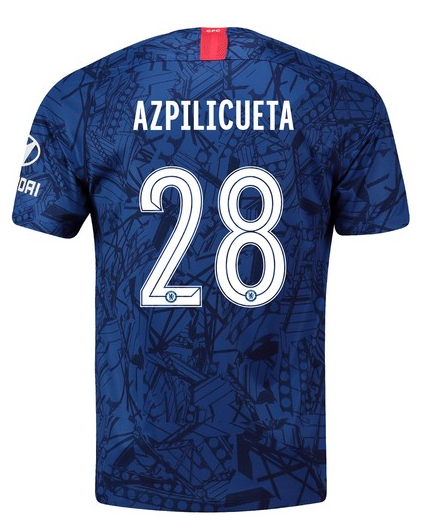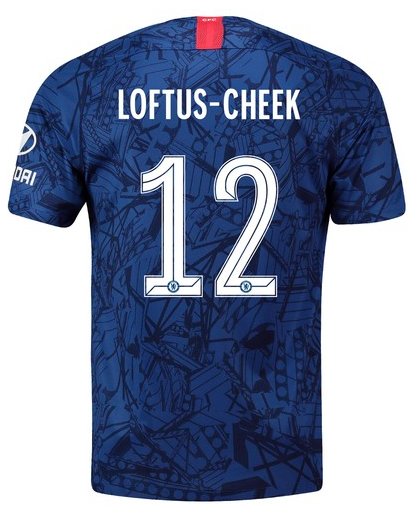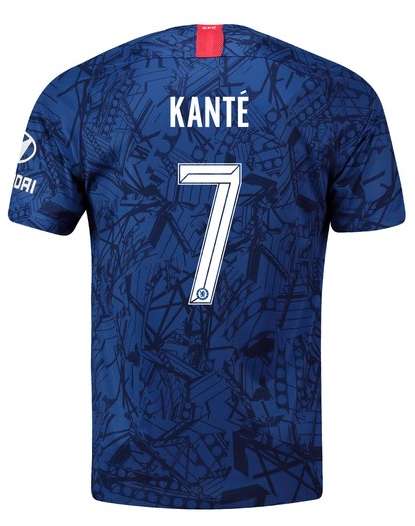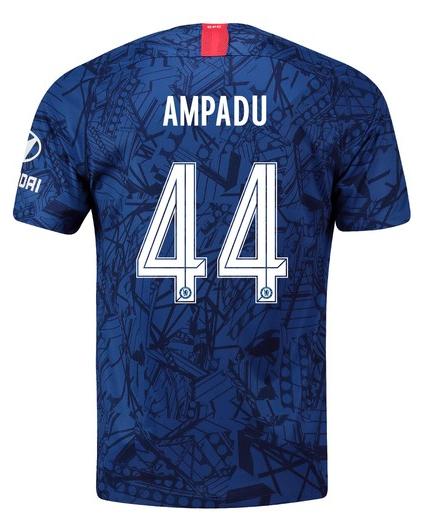
Il font 2019/2020 del Chelsea Lo indosseranno i Blues la prossima stagione, ma non in Premier League
L'Home Kit 2019/2020 del Chelsea è stato uno dei primi svelati da Nike nel corso delle recenti presentazioni che hanno interessato le grandi squadre: la maglia dal pattern decisamente originale è ispirata alle quattro tribune di Stamford Bridge e sarà indossata dai Blues nel corso della prossima stagione, ma non da Eden Hazard che dopo aver fatto da testimonial alla campagna è stato ceduto al Real Madrid.
Il font del Chelsea ricorda molto quello della stagione 2015/2016 e prevede delle linee interne che dividono perfettamente a metà i numeri, che contengono un piccolissimo crest della squadra nella parte bassa. Il font sarà utilizzato soltanto nelle coppe, sia nazionali che non, visto che in Premier League (così come in Liga, ma non in Serie A) c'è un font standard che viene adoperato per tutte le squadre e che non può essere personalizzato.